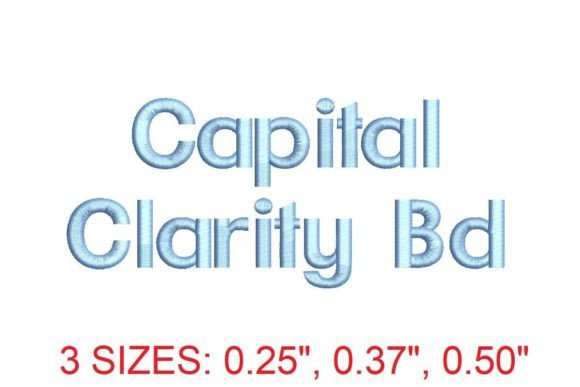
Capital Clarity Bold Font
Encontrar los elementos de diseño adecuados puede ser un desafío, pero Capital Clarity Bold Font ofrece una colección excepcional que eleva tu trabajo al instante.